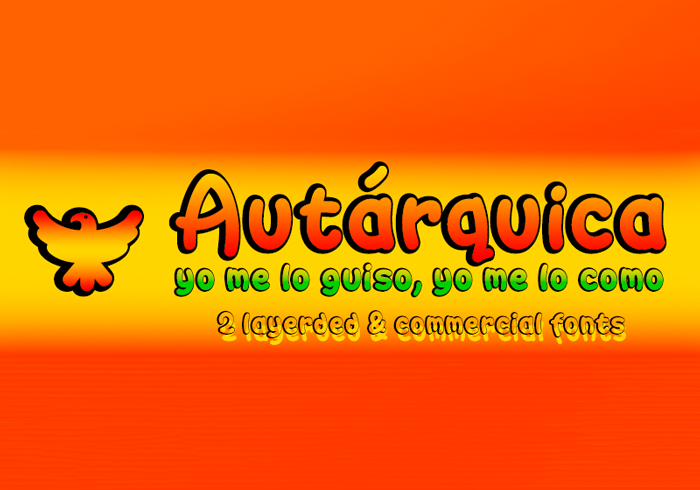
Esta Autárquica font é perfeita para aqueles que buscam uma combinação única de elegância e originalidade na tipografia. Ela foi criada pensando em designers e grafistas que desejam incorporar elementos modernos e tradicionais em suas criações. A fonte inclui duas versões de escrita manuscrita, com um detalhe orgânico no bordo da primeira e uma segunda letra pura que pode ser usada para preencher a primeira. Com essas curvilíneas sutis e fáceis de ler, você pode escrever títulos interessantes ou mensagens publicitárias cheias de estilo. Ela oferece um leque de opções para personalizar suas criações de design, desde escritas de uma só cor até combinações em duas cores. Esta font é perfeita para designers que valorizam o equilíbrio entre simplicidade e criatividade. Se você está procurando por uma fonte que promove tanto a leitura confortável quanto a aparência chamativa, a Autárquica font é seu companheiro ideal. Engane-se se pensar que ela só pode ser usada para títulos grandiosos: com esse design único e vibrante, os designers podem criar um amplo espectro de designs, desde cartazes promocionais até cartas personalizadas. Agradeça por baixar a Autárquica font!